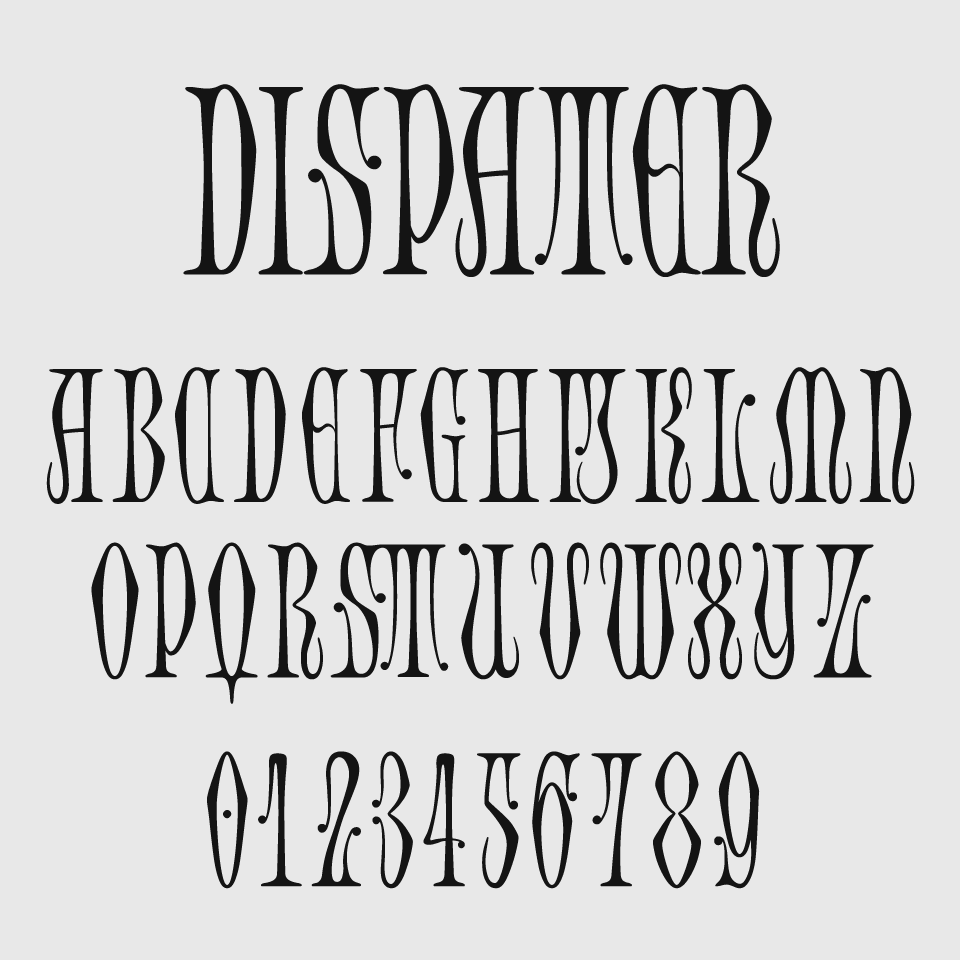
Dispamerフォントは、縦に長く伸びた独特なシルエットが特徴のアール・ヌーヴォー風フォントです。
リズミカルなドロップ状のセリフや、優雅に波打つアウトラインが、アートポスターやクラシック映画のようなレトロで妖艶な雰囲気を醸し出しているユニークなデザインです。
一文字ずつが個性的で、全体としても流麗で装飾的な印象を与えます。高級感や幻想性を求めるグラフィック、イベントのタイトルや表紙などにぴったりで、ロマンチックな演出や印象的なビジュアル作りに効果的なフォントです。
収録文字は、大文字/数字/記号の収録となっています。
| 小文字 | × |